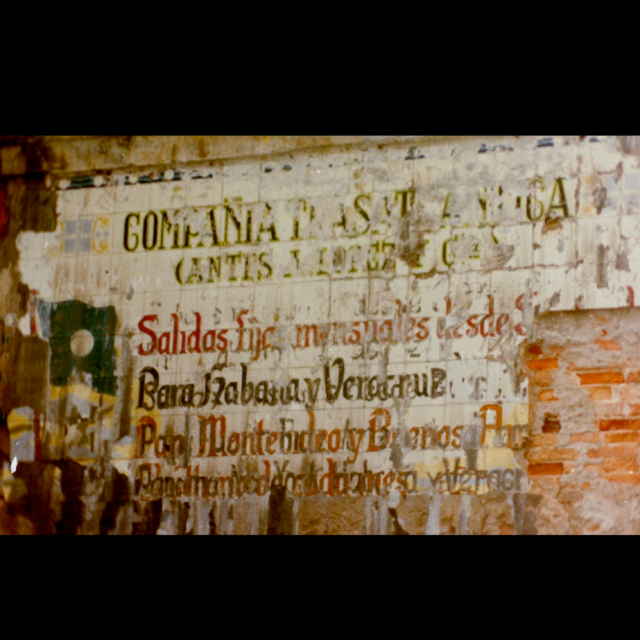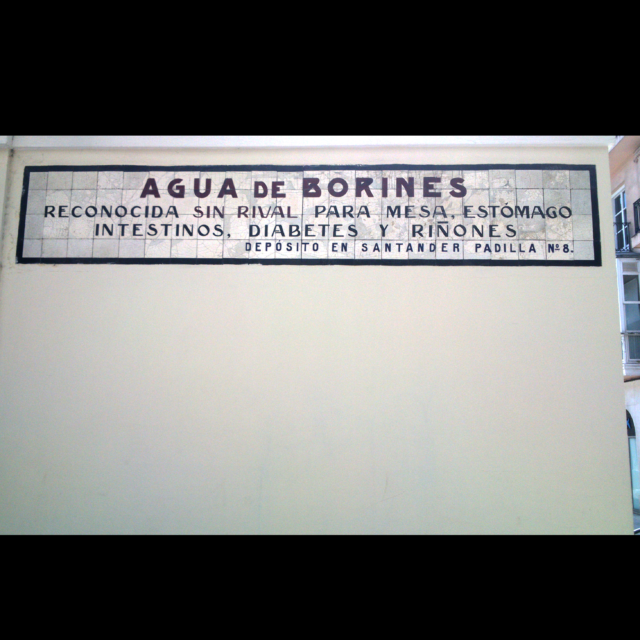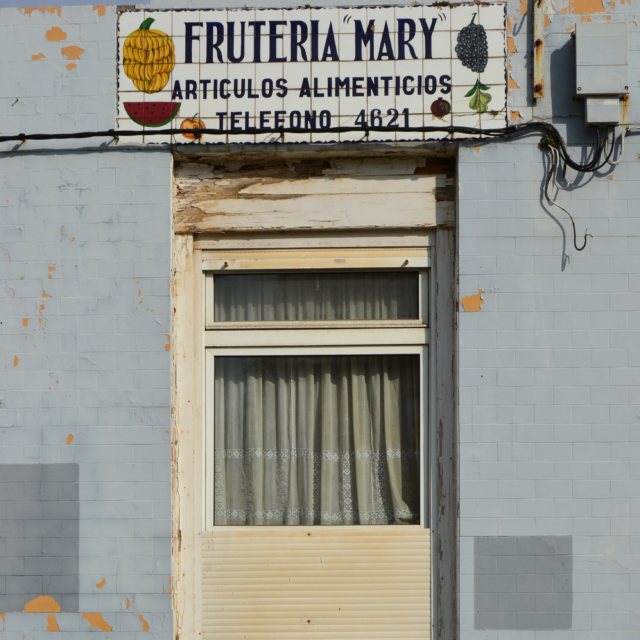
Azulejos del Mercado del Este
Esta semana se cumplen 180 años de la construcción del Mercado del Este, obra realizada por el arquitecto Antonio Zabaleta entre 1839 y 1842. Es de las primeras Galerías comerciales de este tipo que se realizan en España y supuso un cambio conceptual de este tipo de edificios y usos a posteriori.
Aunque con el paso del tiempo se fue deteriorando y quedando en estado de abandono, y en 1986 se inicia su demolición, pero es parada porque se consigue declarar BIC, gracias en parte a una iniciativa de arquitectos y especialistas entre ellos Peridis; En 1997 se inicia  proyecto de reconstrucción por el Arquitecto Carlos Riaño, además concediendo el Premio Nacional de Arquitectura de ese año. Y ya  es en el año 2002 cuando se reabre, preservando fachadas y recreando en su interior tanto trabajo en maderas, forja, suelo y distribución interior a la obra original de Zabaleta. Esto también le supuso un Premio por parte de Hispania Nostra, por la recuperación de tan emblemático edificio.
Recientemente, en la exposición sobre la retrospectiva de Amalia Avia “El Japón de Los Ángeles” donde retrata algunos comercios locales de Madrid, una de las pinturas es precisamente el Mercado del Este de Santander.
Detalle del cuadro de Amalia Avia. Mercado de Santander, 1988.
Uno de los elementos que se han conseguido salvar, en ese proceso de nombramiento de BIC, es la desaparición de algunos anuncios de los paneles de azulejo, que estaban en muy mal estado. Es la única muestra, junto al icónico rótulo de Fruteria Mary de los Castros, que tenemos en Santander en este material.
Estado de los azulejos antes de la intervención. Años 80.
Hoy día podemos disfrutar de ellos, con esas tipografias tan maravillosas, donde nos habla de la importancia de Santander como ciudad Portuaria y como se comenzaba a comercializar a finales de siglo XIX el agua en botella. Esta historia la tenéis en el libro.
• Estado actual de los azulejos.
Este es un buen ejemplo de protección y preservación de nuestro Patrimonio Gráfico, que esperemos, se traslade a otros carteles y rótulos de nuestras ciudades.
Frutería Mary. Santander.